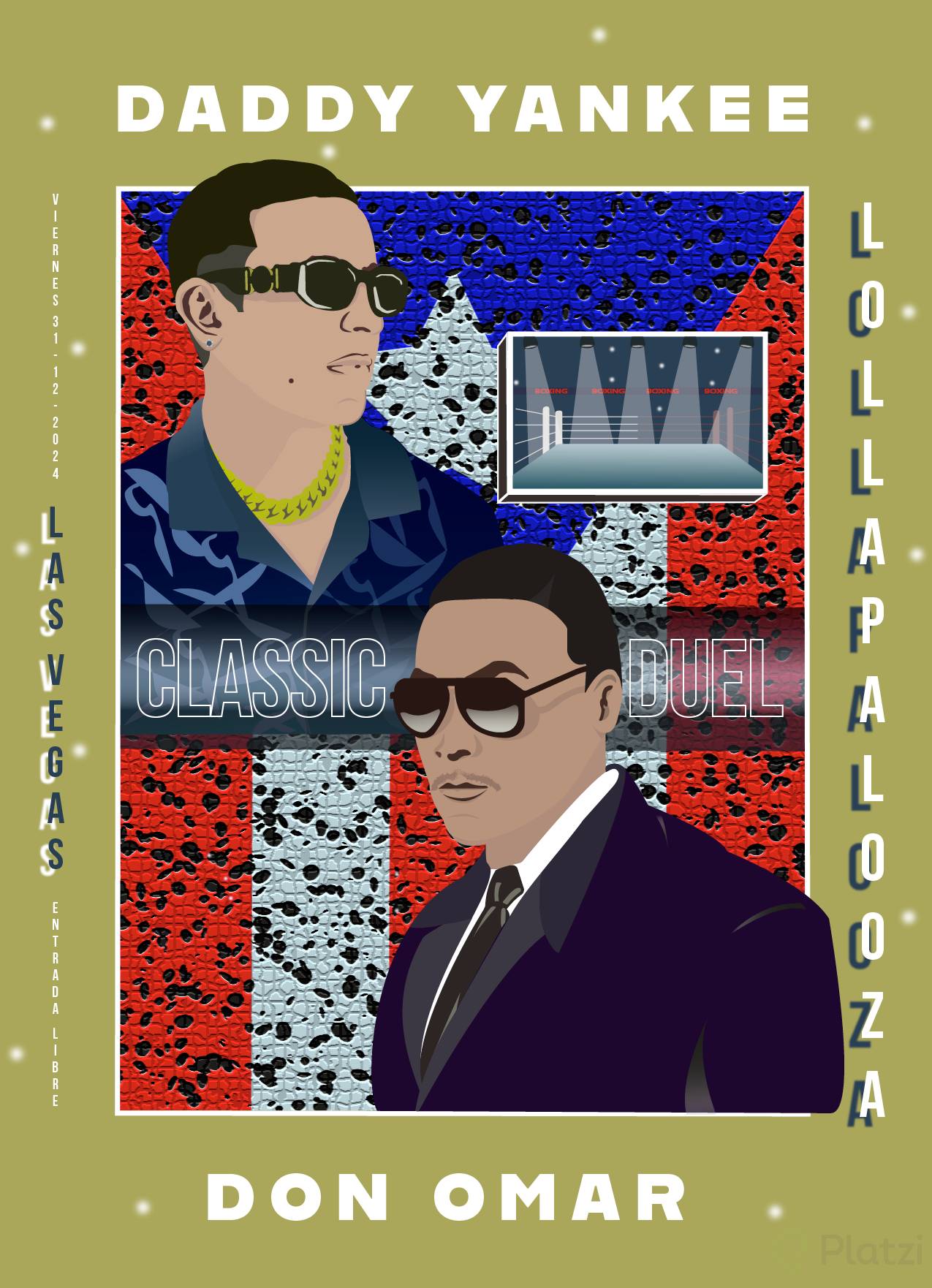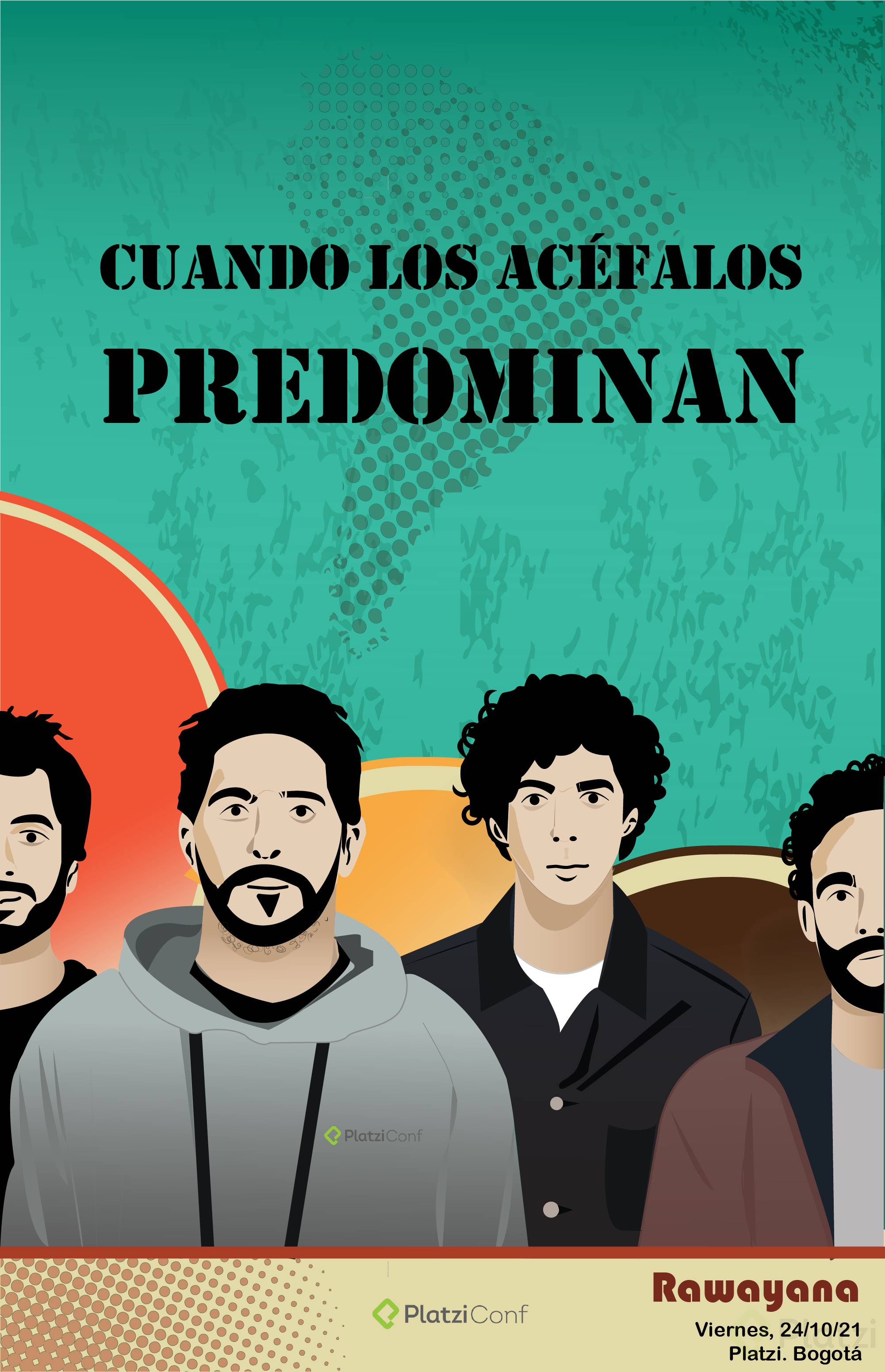
¿Cómo elegir la fuente tipográfica adecuada para nuestro póster?
La elección del tipo de fuente es uno de los aspectos más críticos al diseñar un póster, ya que influye directamente en la narrativa y en la percepción del mensaje que deseamos comunicar. Es fundamental seleccionar una tipografía que no solo sea legible, sino que también refleje la intención del evento de manera contundente.
¿Por qué es importante la legibilidad y coherencia tipográfica?
- Intención clara: La tipografía seleccionada debe reflejar y comunicar claramente la intención del evento. El aspecto visual de las letras puede transmitir distintas sensaciones, desde modernidad hasta nostalgia, lo cual debe alinearse con el objetivo del póster.
- Impacto visual: Un título tipográfico impactante, pero fácil de leer, puede captar la atención de inmediato, sobre todo si se trata de un evento o un artista destacable.
- Uso de herramientas: En programas de diseño como Illustrator, se recomienda marcar las fuentes preferidas como favoritas para facilitar el acceso y evitar perder tiempo buscando entre muchas opciones.
¿Cómo optimizar la composición tipográfica en un diseño?
La disposición y ajuste del texto son vitales para integrar el contenido visual del póster de manera armoniosa y efectiva.
¿Qué técnicas se pueden utilizar para mejorar el diseño del texto?
- Guías y espaciado: Activar guías para asegurarse de que los textos están bien alineados y utilizar el panel de carácter para ajustar el tracking (espaciado entre letras) de acuerdo con el espacio disponible.
- Trabajo con guías: Desbloquear y mover guías en Illustrator permite ajustar la composición con precisión. Es recomendable ocultar las guías temporalmente para evaluar el diseño general sin distracciones.
- Contraste y posición: Colocar texto en posiciones estratégicas y con altos contrastes de color puede crear efectos visuales interesantes, como cuando el texto interactúa con elementos visuales del fondo, como una silueta.
¿Cómo elegir la tipografía correcta para el contexto del póster?
- Pruebas de estilo: Es beneficioso probar diferentes fuentes para ver cuál se alinea mejor con la estética deseada. Fuentes como Abraham Lincoln pueden ofrecer un toque retro, evocando referencias de pósters de épocas pasadas.
- Uso de mayúsculas: Experimentar con el uso de mayúsculas mediante la opción de cambio de mayúsculas y minúsculas, ajustando el tamaño para asegurar que el texto sea legible y proporcional al diseño general.
¿Cómo integrar adecuadamente información adicional y logotipos?
Una vez seleccionada y organizada la tipografía principal, es crucial integrar información adicional, como fechas y lugares, de manera coherente y profesional.
¿Cómo se debe manejar el texto complementario y los logotipos?
- Jerarquización: Utilizar colores y tamaños diferentes para crear jerarquía visual en la información adicional. Esto ayuda a que el espectador pueda procesar rápidamente los detalles importantes, como las fechas y las ubicaciones.
- Guías para la alineación: Al añadir texto complementario, las guías son útiles para asegurar que la información esté alineada correctamente, creando un aspecto cohesivo.
- Colores y jerarquía: Diferenciar texto usando varios tonos puede evitar que compita con el texto principal, mientras añade dinamismo al diseño.
- Logotipos: Integrar logotipos usando vectores libres de problemas de resolución. Respetar el manual de marca es esencial para mantener la integridad visual de cada logotipo. Por tanto, hay que colocar los logotipos sin que compitan visualmente con el texto y asegurando que mantienen el espacio necesario entre ellos.
A medida que avanzas en el diseño del póster, recuerda ajustarlo continuamente hasta lograr que cada elemento esté perfectamente alineado con la intención del mensaje que deseas transmitir. ¡Con perseverancia y dedicación, llegarás a crear un diseño impactante y atractivo!